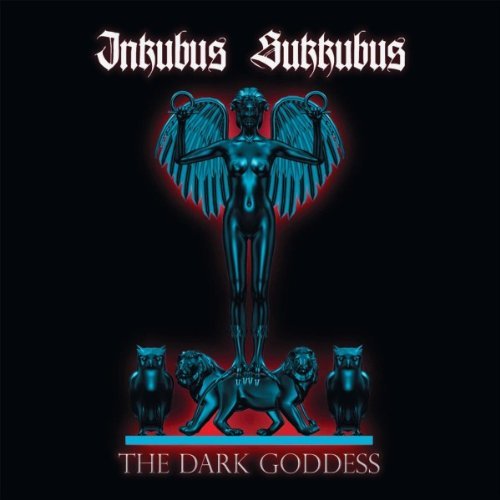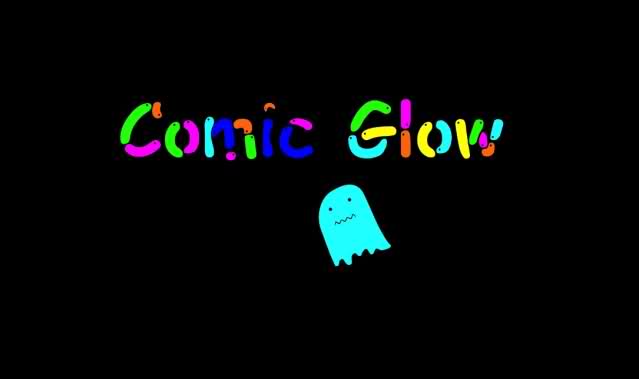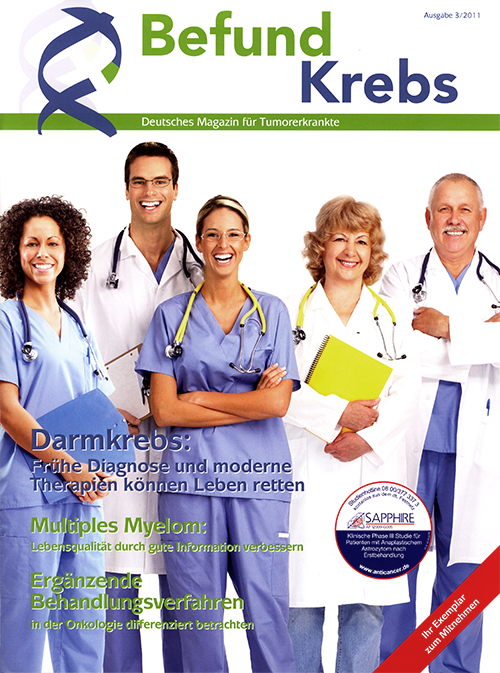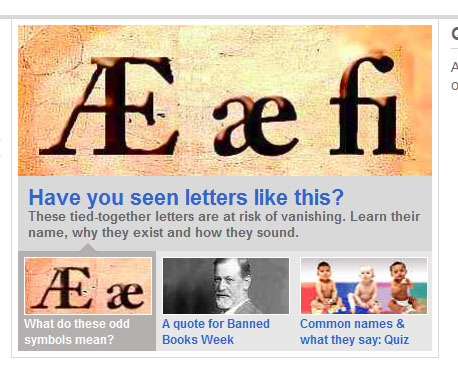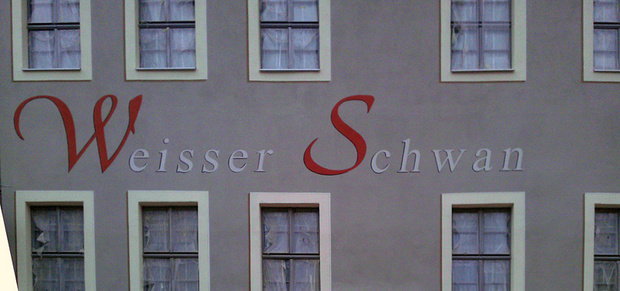
Seltsame Schrift! Schaut Euch mal die unterschiedlichen Buchstabenenden an … :-?
Wenn da mal nicht eine gewisse Agentur aus Hemer am Werke war! :twisted:
Sowas wie Comic Glow schaffe ich ja vielleicht noch :hammer:, aber an Times und Helvetica sollten sich dann wohl die Profis machen ;-)
vielleicht wurde es schonmal gepostet, aber ich bin heute in einer Musikzeitschrift über eine kleine, verschwommene Anzeige für das jüngste Album von Intzubus Sutztzubus gestolpert. Und eine kurze Recherche zu Hause am heimischen PC bestätigte dann die Ahnung:
Selbst eine aus ehem. Grafikdesign-Studenten bestehende Band scheint vor Paul Lloyds »Killigrew« nicht gefeit zu sein. :neenee:
Wie kraß. Was für eine Sprache hat denn tz-Doppelungen auf Lager?
Keine. Die Band heißt Inkubus Sukkubus.
Damit dürfte doch bald das halbe Dutzend an verhunzten Killigrew-Band-Logos voll sein …
Ich glaube, der Bandname ist dem geschätzten Kollegen schon klar … ;-)
Manchmal empfinde ich Phrasen aus dem Englischen doch als sehr nützlich:
This is wrong on so many levels ... :neenee::shock::cry::peng::-?
Gefunden auf dictionary.com. Die »komplette Story« (oder was man dafür hält) findet sich dann hier. Wir befinden uns hier ganz offenbar im Jurassic Park der Buchstaben! :twisted:
Oh weh, hast Du die Leserkommentare zu dem Text auch gesehen …? :shock:
Holy cow! Wir sind des Teufels.
Sowas wie Comic Glow schaffe ich ja vielleicht noch :hammer:, aber an Times und Helvetica sollten sich dann wohl die Profis machen ;-)
Dann musst Du aber auch ein kleines Gespenst als Symbol mit dazu erfinden. :-P
Könnte das als Grundlage dienen? Zusammengesetzt aus lauter lustig-gräßlich leuchtenden Bakterien …
PS: Sorry Kathrin, bessere Geister kann ich nicht so auf die schnelle und ohne Papierskkizze :neenee::roll::schonklar:
Manche Leute schrecken aber auch vor gar nix zurück:
STACHELSCHWEINKALTSCHALE
Ein frisches Stachelschwein aufkochen und durch ein feines Sieb streichen. Dann mit 1 bis 1 1/2 Litern Wasser und Zitronenschale nochmals aufkochen, mit etwas Mehl binden und über süße Makronen anrichten. Etwas für heiße Tage.
HASENSCHWANZ A LA MEYER
Der feinen Zunge von Herrn Erich A. Meyer verdanken wir die folgende Delikatesse. Der gut abgehangene Hasenschwanz wird gewaschen, gesalzen, nebst Petersilie, Sellerie und Wacholderbeeren 4 bis 5 Stunden gedämpft und sorgfältig abgeschmeckt.
Merke: Hasen sind glücklicher ohne Schwanz.
BACKOBST MIT GÜRTELTIERKLÖSSCHEN
Backobst über Nacht quellen lassen und am nächsten Morgen mit reichlich Zimt und einer Zitronenschale auf kleiner Flamme langsam gar kochen. Für die Zubereitung der Gürteltierklöße hält man sich genau an das Rezept für Kartoffelkloesse, nur dass statt der Kartoffeln Gürteltiere verwendet werden. Zum Formen des Kloßes befindet sich die linke Hand unter, die rechte Hand jedoch über demselben. (1,3,4)
Merke: Zimtsterne, von Mutter handgesägt, schmecken immer noch am besten!
Tumor ist wenn man trotzdem lacht …